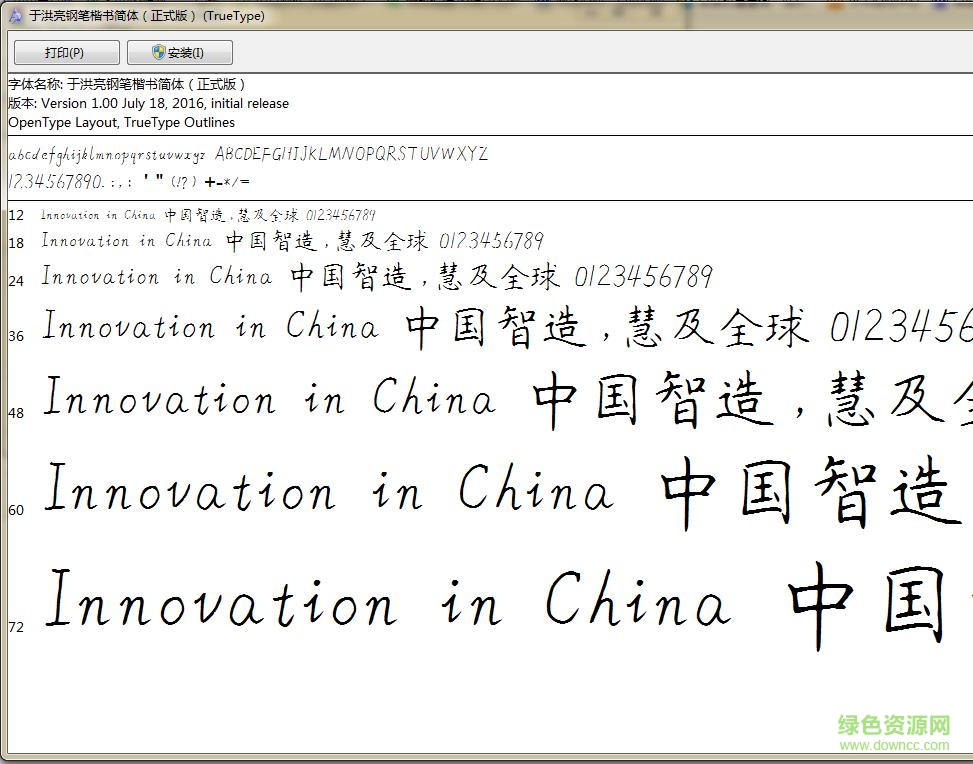
神韻于洪亮楷書(shū)
神韻于洪亮楷書(shū)ttf是一款十分不錯(cuò)的楷體字體,讓你能夠感受到端正的字體樣式風(fēng)格,更能夠?qū)崿F(xiàn)眾多藝術(shù)字效果,幫助你更好的完成各項(xiàng)媒體制作工作,快來(lái)綠色資源網(wǎng)下載吧!
神韻于洪亮楷書(shū)是一款神韻字體中的楷書(shū)字體,這款字體,讓你能夠獲得不同的楷書(shū)字體使用體驗(yàn),運(yùn)用到書(shū)寫(xiě)以及閱讀中都能夠帶來(lái)不同的體驗(yàn)!
神韻于洪亮楷書(shū)字體介紹
1、所謂"波",指筆畫(huà)左行如曲波,后楷書(shū)中變?yōu)槠?;所謂"磔"只右行筆畫(huà)的筆鋒開(kāi)張,形如"燕尾"的捺筆。
2、省減筆畫(huà)結(jié)構(gòu)等等。其中以橫向取勢(shì)和保留毛筆書(shū)寫(xiě)自然狀態(tài)兩面點(diǎn)最為重要。
3、毛筆的柔軟性以使?jié)h字筆畫(huà)產(chǎn)生了粗細(xì)方圓。藏露等各種變化。還有字距寬。行距窄也是其章法上的一大特點(diǎn)